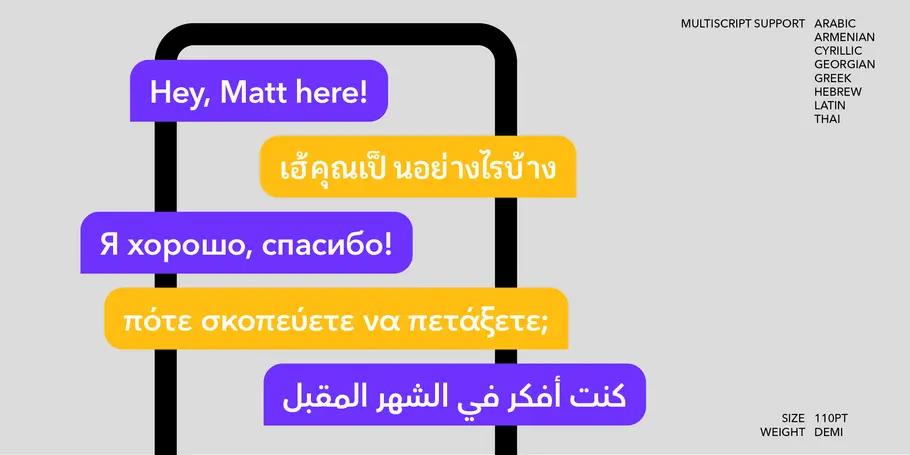
Avenir® Next World
Design ohne Grenzen.
Avenir® Next World, die jüngste Schriftveröffentlichung von Monotype unter der Leitung von Akira Kobayashi, ist eine umfangreiche geometrische Sans-Familie, die Texte in über 150 Sprachen darstellen kann.
Kobayashis maßgebliche Rolle bei zurückliegenden Adaptionen und Weiterentwicklungen von Avenir, seine Sprachkenntnisse sowie sein Verständnis für die Designphilosophie des Originalschöpfers Adrian Frutiger waren die beste Voraussetzung dafür, die umfangreiche Spracherweiterung der Familie künstlerisch zu leiten.
Avenir Next World bietet 10 Strichstärken, von Ultra Light bis Extra Black, sowie dazu passende Italic-Schnitte, die allerdings nicht die arabischen, georgischen und Thai-Zeichensätze unterstützen, da das kursive Schreiben in diesen Sprachregionen keine Tradition hat. Separate nicht-lateinische Subfamilien, die nur die arabische, kyrillische, georgische, hebräische oder thailändische Schrift unterstützen, sind für all jene Anwender und Anwenderinnen erhältlich, die nicht die volle Sprachunterstützung benötigen.
Avenir gehört seit Jahrzehnte zu den beliebtesten Schriften in der Markenkommunikation, weil ihr unaufdringlicher Ausdrucksstil geschätzt wird, der zu allen Produkten und Marken mit einem klaren Image passt. „Ihre Buchstabenformen sind bezüglich der Lesbarkeit sehr präzise entworfen, so dass sie die Aufmerksamkeit des Lesers nicht vom Text ablenkt“, erläutert Kobayashi eines der Erfolgsgeheimnisse der Familie.
Die Original-Avenir wurde 1988 von Adrian Frutiger entworfen. Ihr Name bedeutet im Französischen „Zukunft“ und deutet auf den Einfluss von Futura auf das Avenir-Desigkonzept hin. Im Gegensatz zu Futura ist Avenir allerdings nicht streng geometrisch konstruiert.
So sind beispielsweise die vertikalen Striche kräftiger angelegt als die horizontalen, das o ist kein perfekter Kreis und die Oberlängen sind verkürzt. Diese Nuancen unterstützen die Lesbarkeit und verleihen Avenir ein harmonisches Erscheinungsbild, sowohl für Texte als auch für Überschriften.
Im Jahr 2002 erweckte Akira Kobayashi zusammen mit Adrian Frutiger die Avenir zu neuem Leben. Mit Avenir Next wurden nicht nur manche Buchstaben vorsichtig korrigiert, sondern die Familie erhielt eine komplett neue Aufteilung der Strichstärken sowie die Ergänzungen Ultralight und Heavy. Eine etwas stärker geneigte Italic gab der Schrift Dynamik und neue Kapitälchen wie auch Mediävalziffern erweitern die Einsatzmöglichkeiten.
Ebenfalls neu bei Avenir Next waren Condensed-Schnitte, mit denen sich die Schrift platzsparender einsetzen ließ. Das Design von Avenir Next erfreut sich bis heute großer Beliebtheit. Doch die Schrift war nicht nur im Druck erfolgreich. Dank des erweiterten Zeichenumfangs und der verzüglichen Bildschirm-Optimierung fasste die Schrift auch im digitalen Umfeld Fuß, bis hin zur Systemschrift in Apples MacOS und iOS.
Viele Unternehmen und Marken setzen Avenir im Corporate Design ein oder entwickelten ihr Logo mit der Schrift. Avenir Next World, die jüngste Veröffentlichung von Monotype unter der Leitung von Akira Kobayashi, ist eine umfangreiche Familie, die Unterstützung für mehr als 150 Sprachen bzw.
Schreibsysteme bietet … neben Latin sind das Kyrillisch, Griechisch, Hebräisch, Arabisch, Georgisch, Armenisch und Thai. Kobayashis tiefe Vertrautheit mit der Designphilosophie von Adrian Frutiger sowie den weltweit verbreiteten Schriftsystemen qualifizierten ihn auf einzigartige Weise, das Hinzufügung neuer Sprachen zur Familie zu leiten.
Creative Type Director Akira Kobayashi has three decades of experience, with an extensive background in Japanese typeface design and a deep understanding of calligraphy. After studying at Musashino Art University in Tokyo for four years, Akira Kobayashi accepted his first job at phototypesetting manufacturer Sha-Ken Co., where he was involved in the lengthy and intricate process of designing Japanese fonts.
Akaki Razmadze is from Tbilisi, Georgia. During his studies, he completed an internship at Monotype (Bad Homburg, Germany), where he worked to develop Georgian versions of various Monotype’s typefaces; among them were Helvetica, Meta and so on.
Several Georgian typefaces designed by him, which are distributed for free, are very popular in Georgia. His first typeface Archy can be found on book covers, posters, TV programs, various advertisements and so on.
Graphic designer and type designer based in Bangkok. Buzzed in type design arena under guardianship of legendary Tony Dispigna in New York. His fonts have been used in magazines, book covers, consumer products, record covers, as well as identity for a worldwide company.
He also was a writer and contributor for Thai magazines such as Image, DNA, Freeze and art4d. His typographic work has been recognized by the Type Directors Club, New York. He also teaches graphic design at Chulalongkorn, Bangkok University, and is a visiting lecturer at Rangsit University.